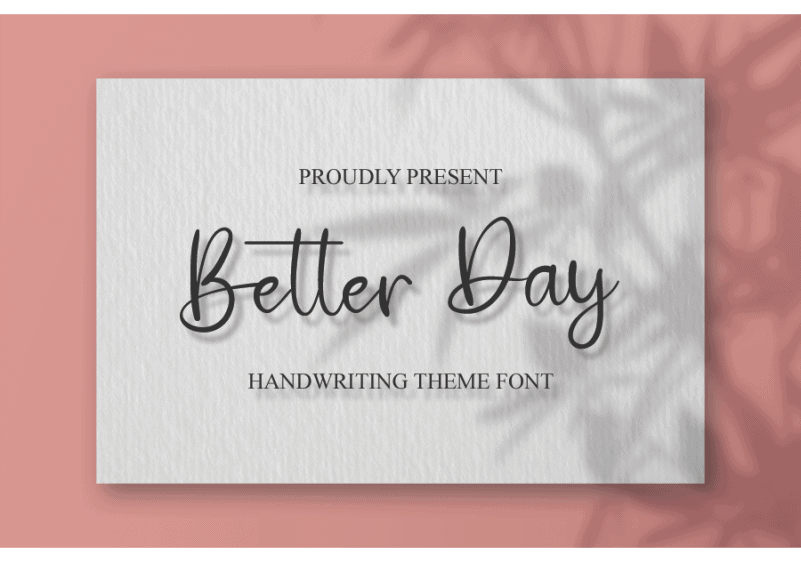
Better Day Script Font – Fonte Grátis
Better Day Script Font
A Better Day Script Font é uma elegante fonte escrita à mão que se destaca por sua originalidade e refinamento. Perfeita para aqueles projetos necessitando de um estilo personalizado, como convites de casamento, cartões de agradecimento, anúncios de casamento, cartões de boas-vindas, logotipos ou qualquer outra criação onde uma pitada de mão-diligente é desejada. Esta fonte escrita à mão não apenas enriquece seu design com um toque único e sofisticado, mas também permite que você exiba a sua personalidade e criatividade através das letras mais importantes em cada projeto. Seja para um evento íntimo ou uma grande festa de casamento, essa fonte escrita à mão é definitivamente capaz de transformar qualquer design com seu encanto singular.